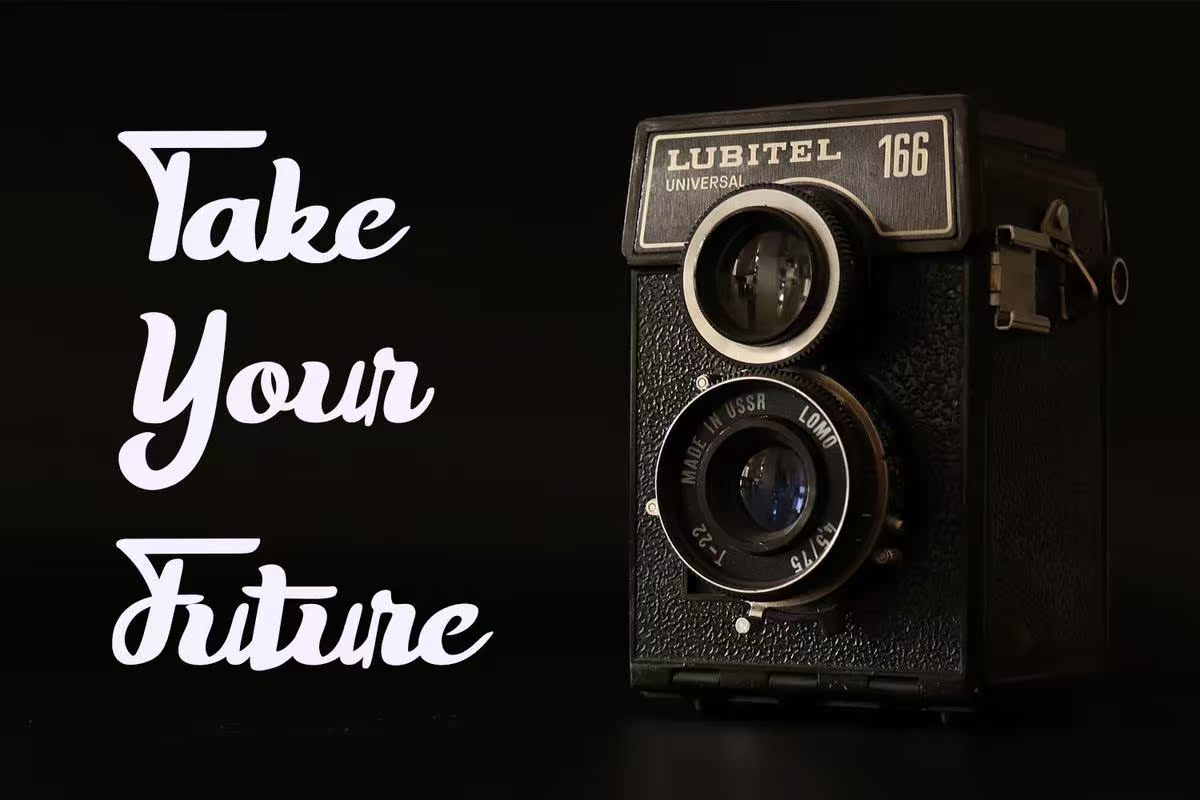
简介:新版脚本字体“跟踪器”。具有开放式功能,可进行文字编辑。跟踪器最常用于标识、标题、封面、海报、徽标、报价、产品包装、标题、商品、社交媒体和问候卡以及许多内容。此字体还支持多语言。要访问替代文字,您需要一个支持字体功能的程序,如Adobeillustratorcs、AdobePhotoshopCC、AdobeIndesign和CorelDraw。介绍一种新的手写字体“跟踪器”。带有OpenTypeFeatures,带有图形学和Swash,这有助于您更好地阅读。跟踪器最常用于标识、标题、封面、海报、徽标、引用、产品包装、标题、商品、,社交媒体和问候卡以及许多其他功能。此功能也支持多种语言。要访问替代项,您需要一个支持以下功能的程序:Adobeillustratorcs、Adobeiphotoshopcc、AdobeIndesign和CorelDraw。